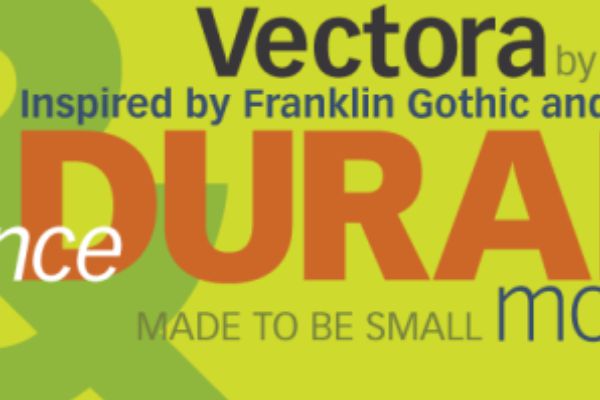
Vectora® Pro 96 Black Italic
Vectora 是一款轻盈且平衡的无衬线字体,赋予文本易读性和和谐的外观 , 可以在小尺寸下轻松阅读,非常适合作为正文的排版字体。报纸、杂志和书籍都可以很好地利用 Vectora 进行布局,是优雅、现代的选择。它也逐渐进入了 logo 字体领域,凭借其异常高的品质,非常适合企业品牌推广。